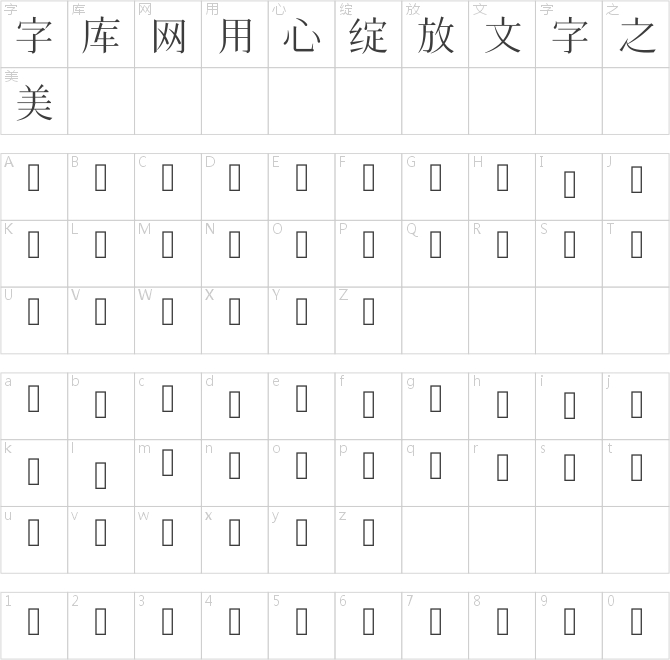
花園明朝字體下載HanaMin
日本花園明朝體在免費字體中算是非常非常好的一款了,花園明朝 (Hanazono) 是一個免費字體,為 GlyphWiki 所研發(fā),字形數(shù)量共 45090 + 47186 個,幾乎收錄了所有漢字字形(但看起來沒有區(qū)分不同地區(qū)標準字形)。 一共收錄了八萬多漢字的免費字體,本次發(fā)布的是八萬漢字完整版。 第一步這個字體的輪廓是用 CHISE 計劃的影系統(tǒng)生成的,數(shù)據(jù)來源就是 Glyphwiki,因此可以在相對短的時間內生成N多的文字(貌似今年剛補完日本的戶籍統(tǒng)一文字),但是影系統(tǒng)生成的筆畫輪廓實在是不敢恭維,其避讓系統(tǒng)也不算很完善,不能用來生成很粗的字。